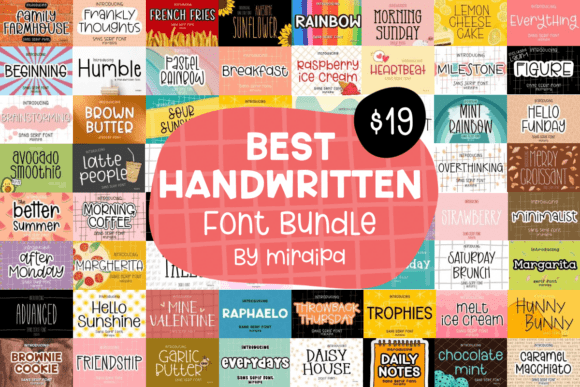
Best Handwritten Font Bundle
Best Handwritten Font Bundleのような高品質の素材をお探しの場合、このプレミアムパッケージはクリエイティブなプロジェクトに素晴らしい選択です。
POD(オンデマンド印刷)製品、結婚式の招待状、またはソーシャルメディアのグラフィックを作成している場合でも、Best Handwritten Font Bundleは理想的です。